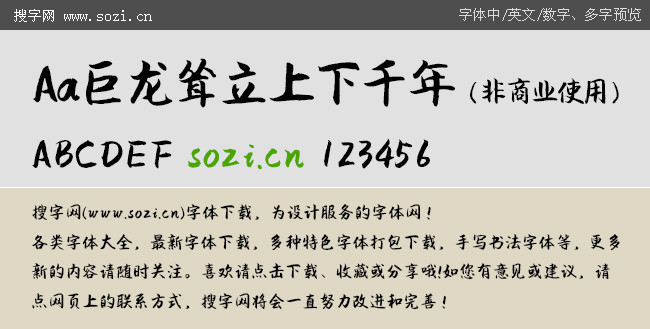
Aa巨龍聳立上下千年(非商業(yè)使用)
搜字網(wǎng)給大家提供一款A(yù)a巨龍聳立上下千年(非商業(yè)使用)中文字體下載,該字體是一款手寫中文字體,這款字體筆觸粗細適中,字形端莊,書寫靈動飄逸,適合包裝設(shè)計、書裝設(shè)計、海報設(shè)計等應(yīng)用(此字體為個人非商用版,商用可以聯(lián)系QQ:1006760504)。